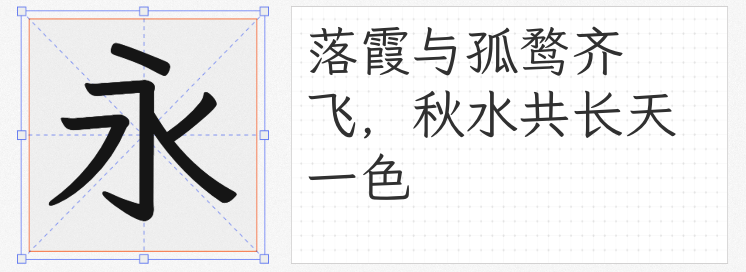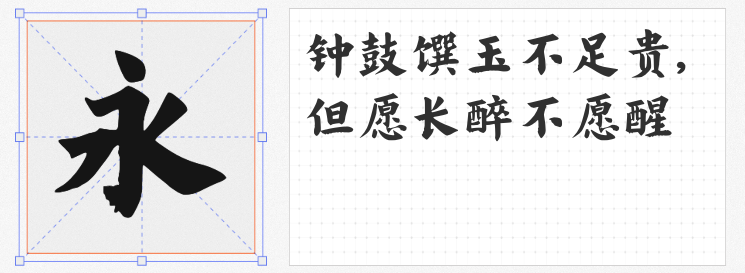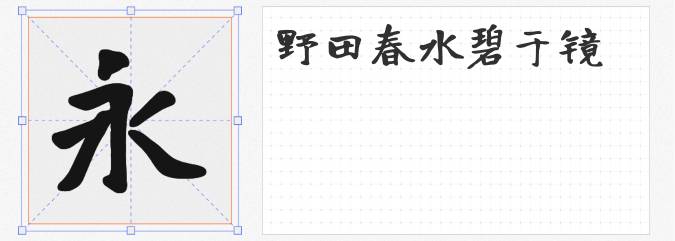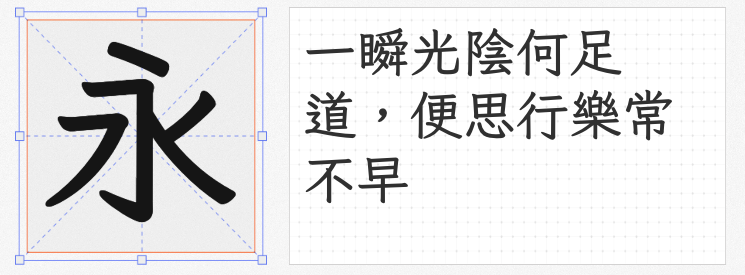
在平面设计与数字创作中,书法字体以其独特的笔触韵律与文化底蕴,成为提升作品格调的核心元素。本文精选四款开源且可免费商用的书法字体,涵盖繁体传承、国标规范、刚劲庄重等多元风格,助力设计师突破版权限制,释放创意潜能。
作为霞鹜文楷的繁体中文版本,霞鹜文楷 TC Medium以「传承字形标准化文件」为基准,对部件结构进行深度优化。其字形保留康熙字典体的古雅韵味,笔画转折处融入楷书顿挫感,横细竖粗的对比强化视觉层次。该字体特别适合古籍排版、文化类海报及传统品牌设计,例如在茶文化主题的宣传物料中,其古朴字形与水墨背景相得益彰。技术层面,霞鹜文楷 TC Medium支持CJK统一表意文字扩展A区,覆盖繁体中文常用字集,确保排版完整性。
针对中国大陆设计场景,霞鹜文楷等宽 GB Regular严格遵循《通用规范汉字表》笔形标准,对原霞鹜文楷进行系统性修正。其等宽特性使其成为代码编辑器与数据可视化设计的理想选择,而6.5:1的宽高比在长文本阅读中保持舒适呼吸感。在少儿读物排版中,该字体通过规范化的笔画结构降低儿童认知负担,同时以仿宋与楷书融合的刚柔并济风格,营造温馨的阅读氛围。
基于开源字体「有字库龙藏体」拓展的Bold版本,通过增加字重与笔锋力度,塑造出碑刻般的厚重质感。其竖画末端的悬针处理与横折处的方角转折,形成强烈的视觉冲击力,特别适用于电影海报标题、品牌LOGO等需要强调存在感的场景。在2024年某武侠游戏宣传片中,该字体成功传递出「十步杀一人,千里不留行」的江湖气魄。
以粗字重与规整结构为特征,程荣光刻楷通过均衡的笔画分布与适度的字面率控制,在庄重感与可读性间取得精妙平衡。在政府公文、学术著作封面等正式场合,其严谨字形传递权威性与专业性;而在婚礼请柬、纪念册等情感化设计中,略带装饰性的捺画收笔又为整体增添人文温度。